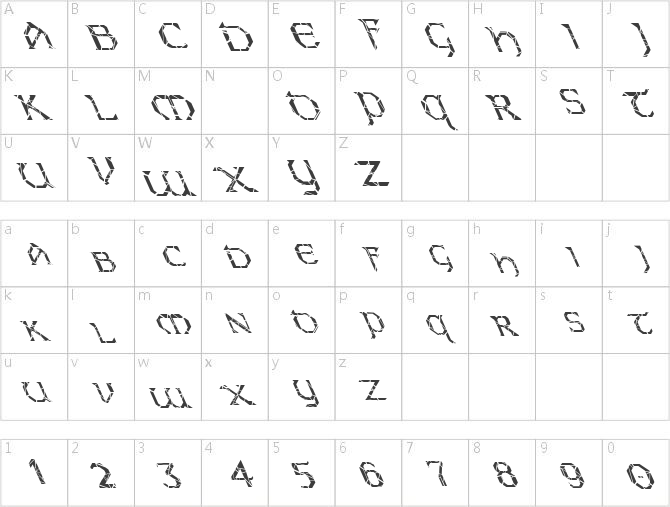
FZ JAZZY 31 CRACKED LEFTY
FZ JAZZY 31 CRACKED LEFTY介绍
FZ JAZZY 31 CRACKED LEFTY字体字库是一款让人赏心悦目、百看不厌的英文字体,适合各类广告和产品包装设计应用,字体大小0.09MB,格式为ttf字体,上传用户是快霸中国,作者/版权方为未知
FZ JAZZY 31 CRACKED LEFTY效果图